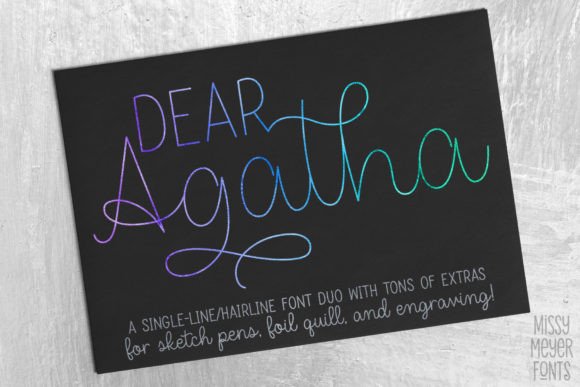
Dear Agatha (single Line)
Mencari elemen desain yang tepat bisa jadi sulit, namun Dear Agatha (single Line) menawarkan koleksi luar biasa yang akan langsung meningkatkan kualitas karya Anda.
Baik Anda membuat produk POD (Print on Demand), undangan pernikahan, atau grafis media sosial, Dear Agatha (single Line) adalah pilihan yang sangat ideal.